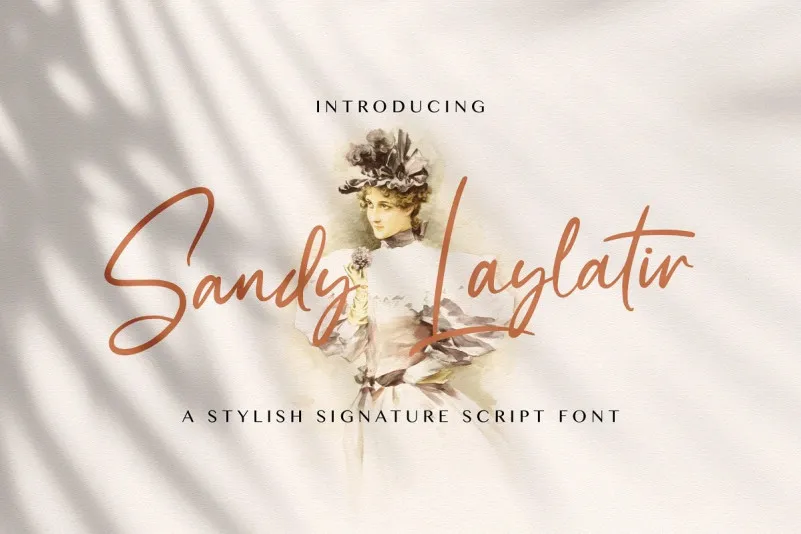
Sandy Lailyatir Script Font – Fonte Grátis
Sandy Lailyatir Script Font
A Sandy Lailyatir Script Font é uma elegante e moderna fonte tipográfica que se destaca por sua beleza e classe. Seu design bem equilibrado faz dela um recurso versátil para projetos criativos, enriquecendo qualquer ideia original com seu charme único. Esta fonte se torna a escolha perfeita quando você precisa de uma fonte que possa se adaptar a múltiplos estilos, desde designs mais tradicionais até os mais modernos e inovadores. Com Sandy Lailyatir Script Font, suas criações ganham um toque especial que as torna ainda mais memoráveis. Experimente incorporá-la aos seus projetos de design gráfico para testemunhar o poder do seu impacto imediatamente.